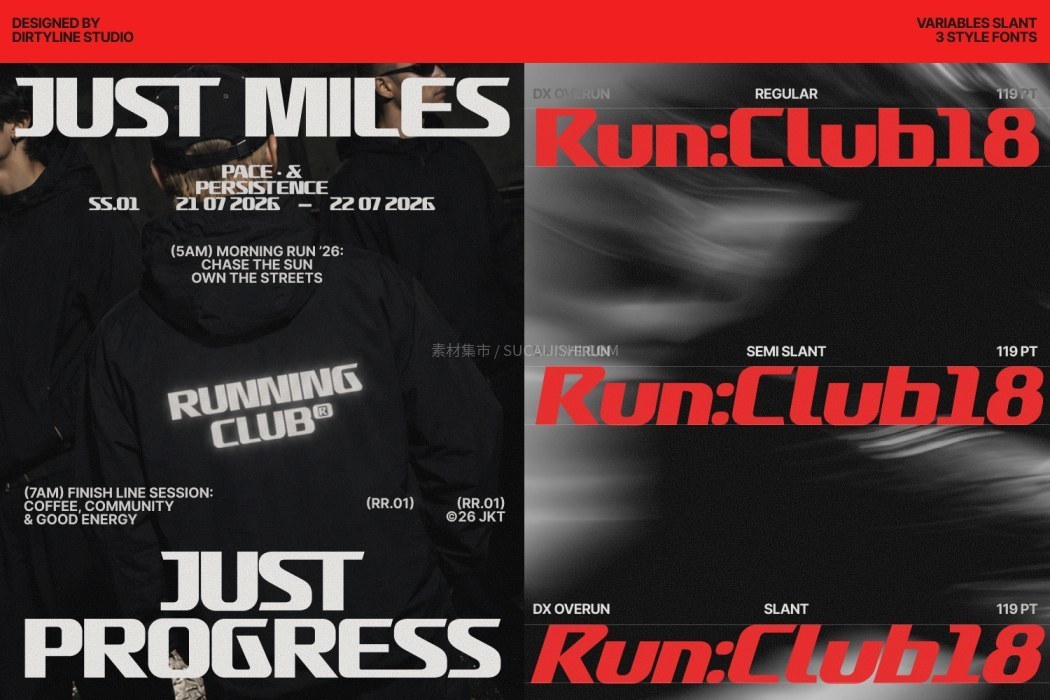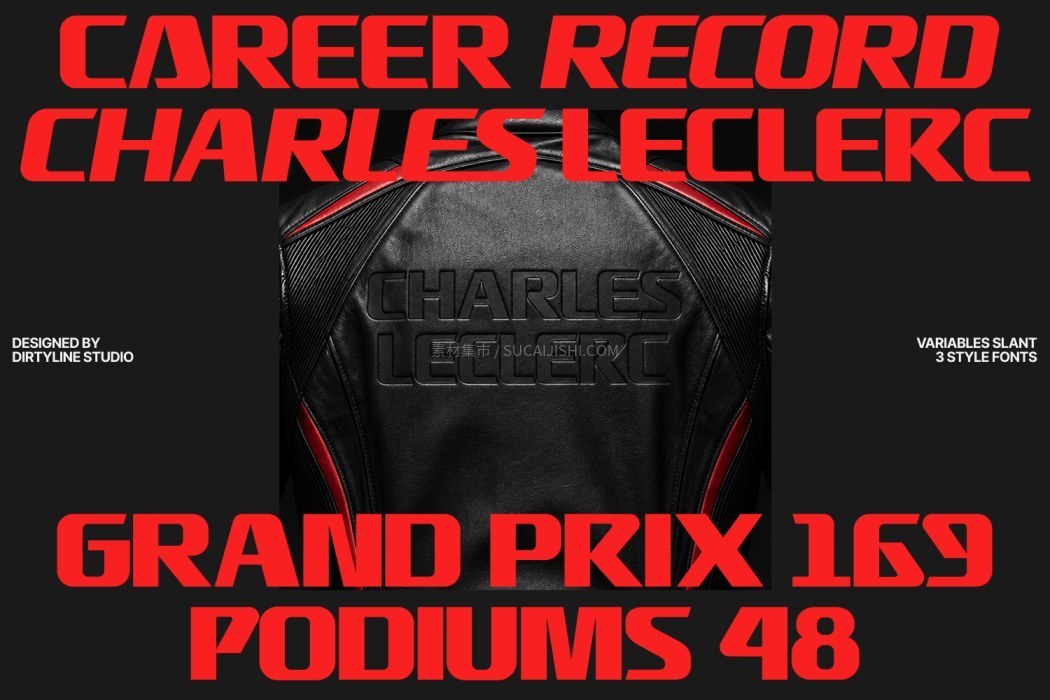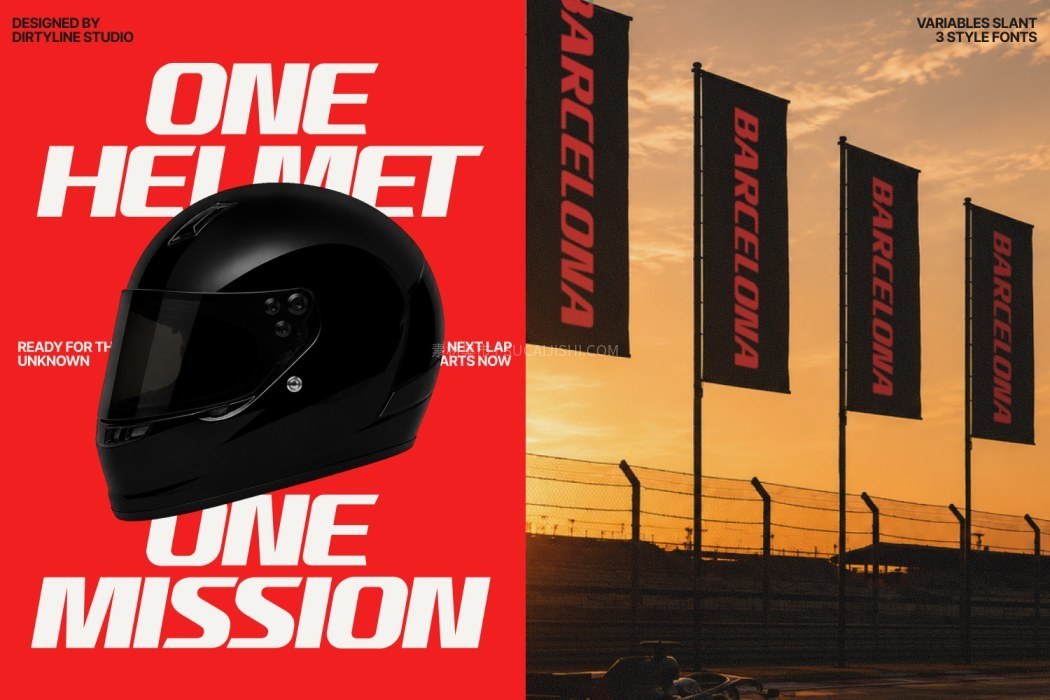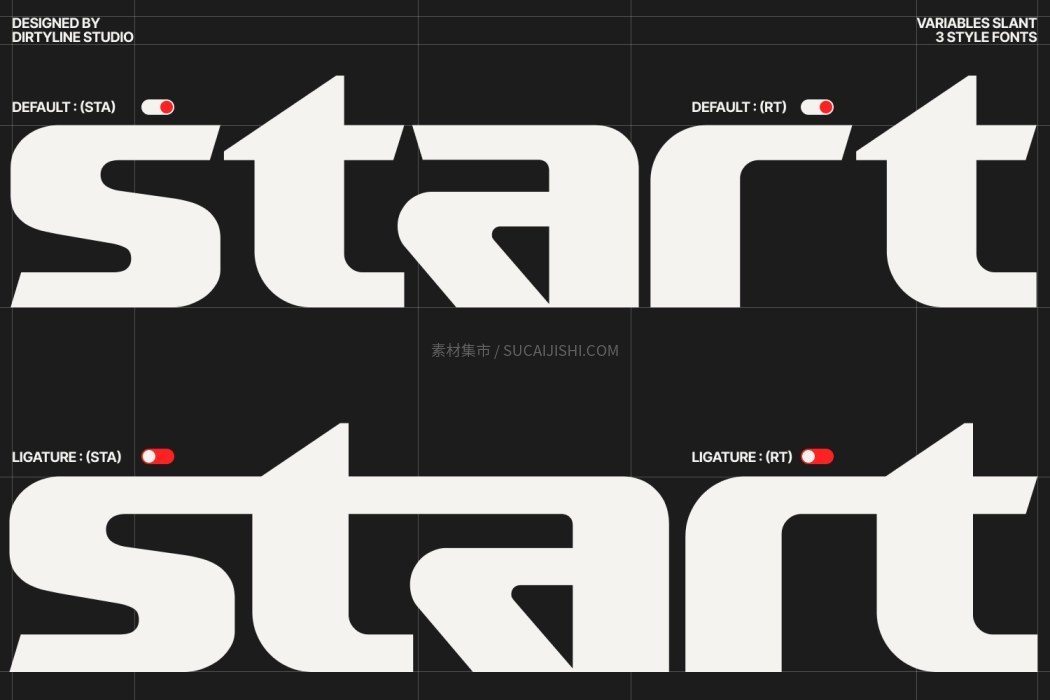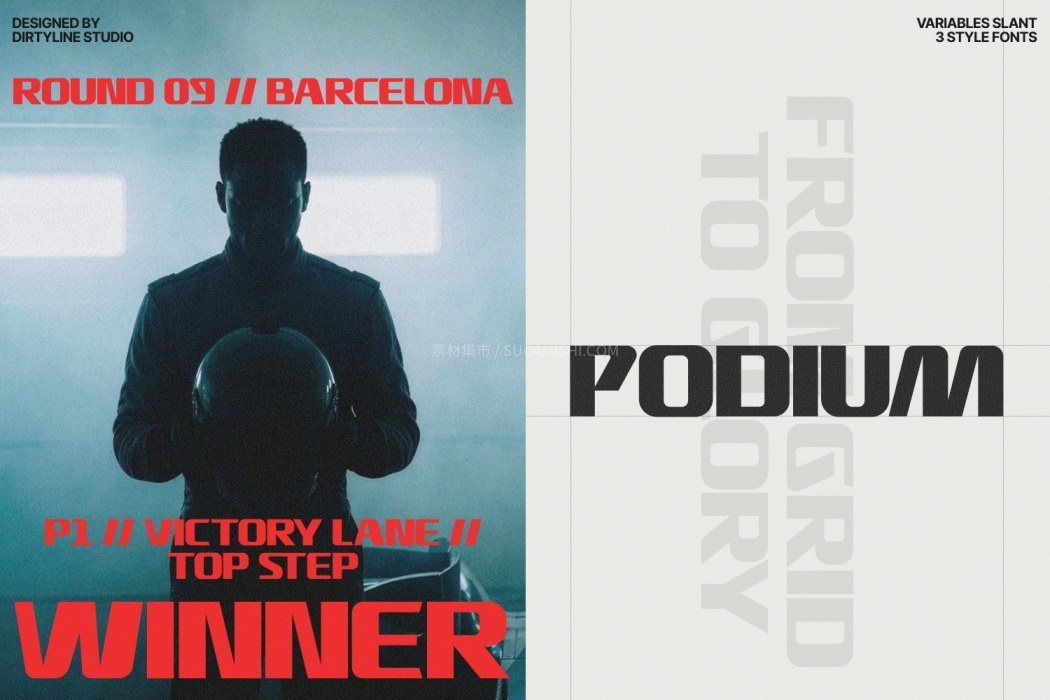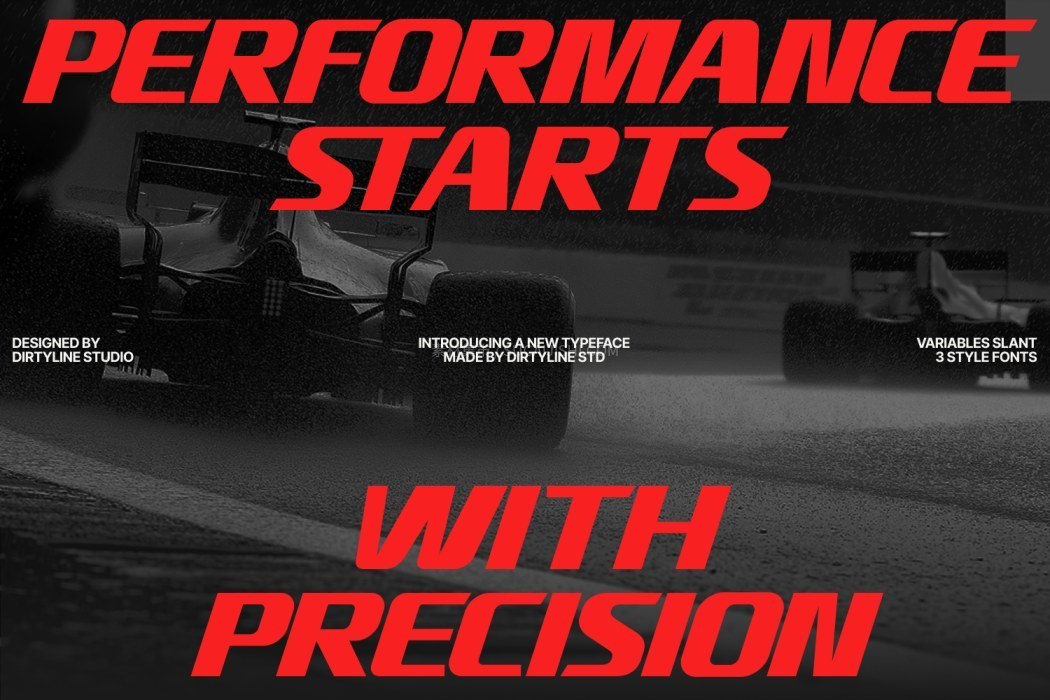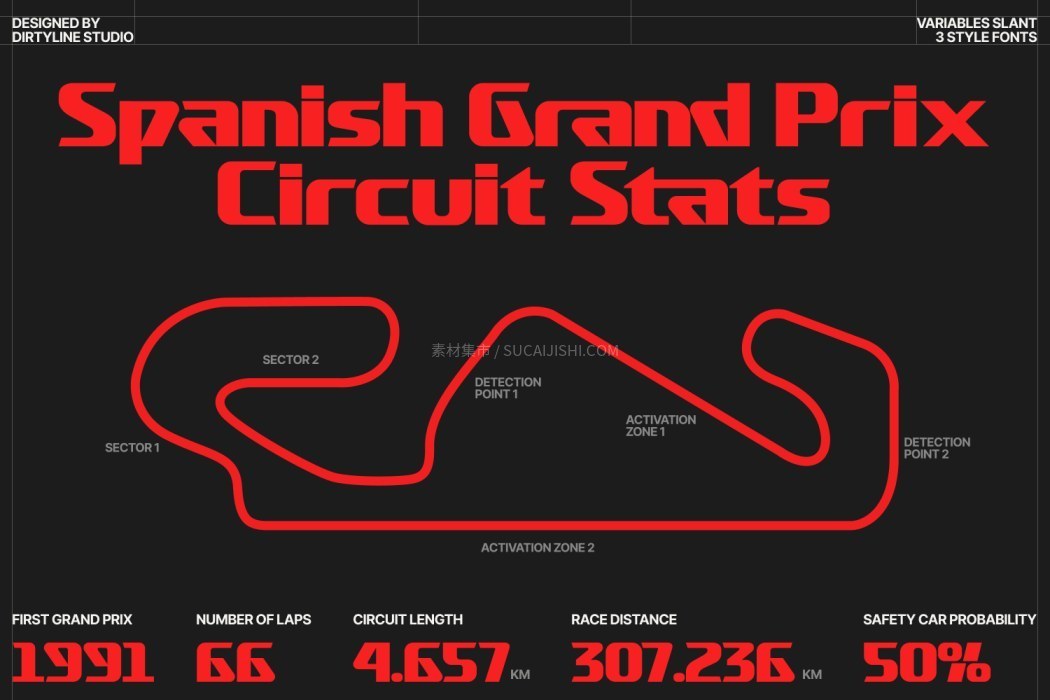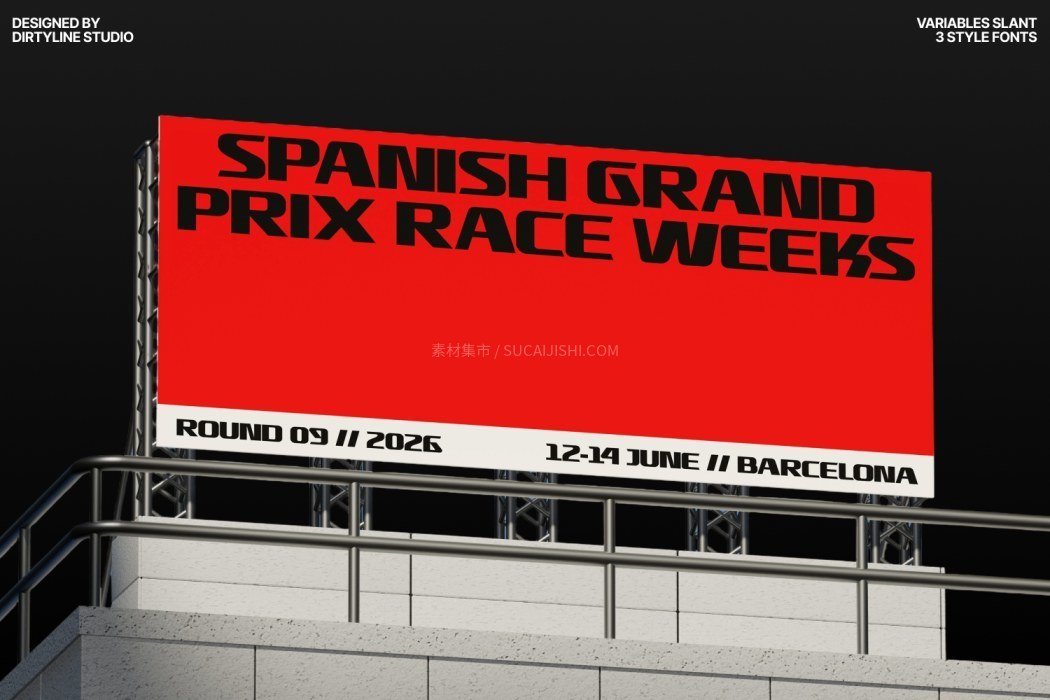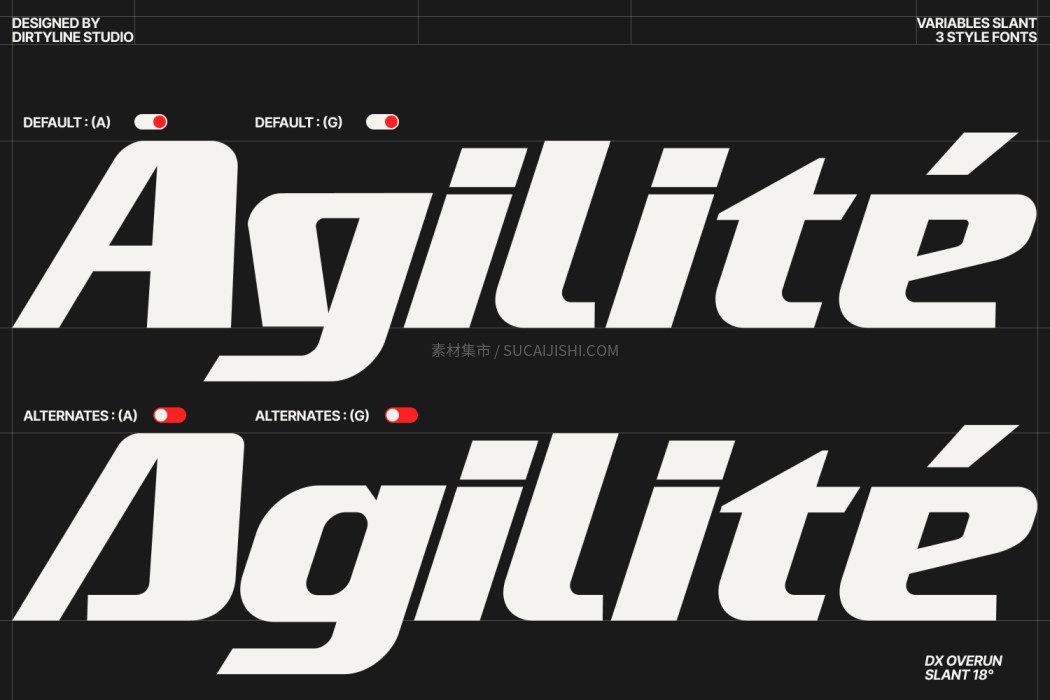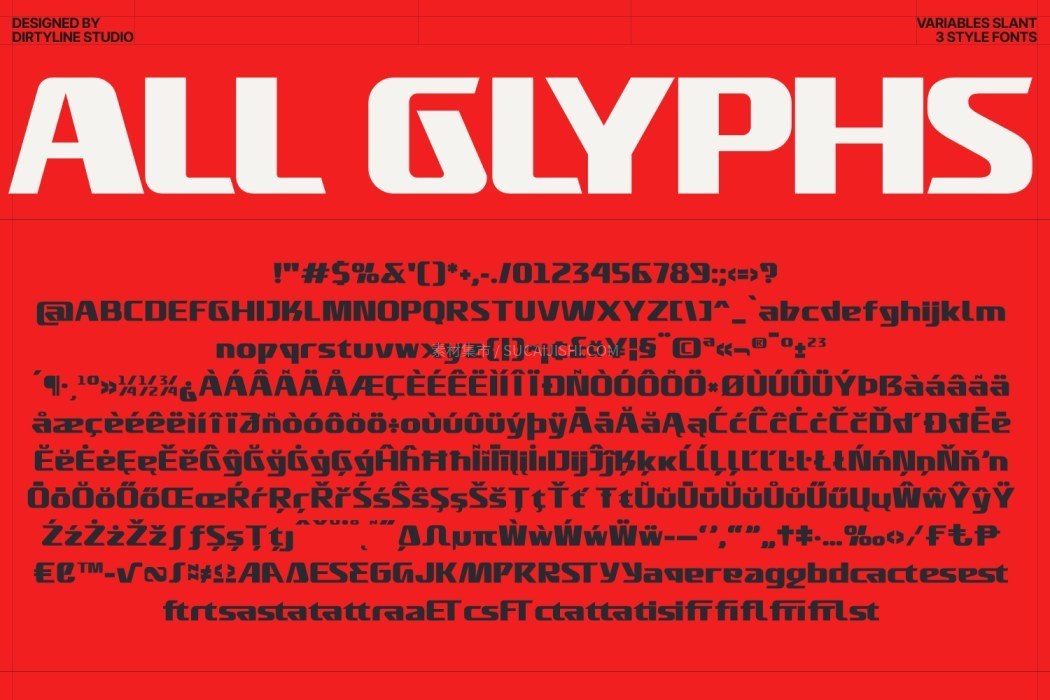
DX Overrun竞速机甲风赛车可变字体
这款字体简直把“速度与激情”刻在了DNA里!它不仅自带一种霸气侧漏的高性能机甲感,还有宽阔厚重的字形和充满空气动力学的倾斜角度,锐利的几何切割让每一个字母都充满爆发力!这套全能字体包含了 3 种精美样式,并且支持超灵活的可变倾斜角度调节,还带有多语言支持和独特的风格替代字形。不管是做赛车运动Logo、电竞赛事海报、汽车品牌视觉,还是潮牌运动服、游戏UI和酷炫的社交媒体排版,它都能轻松拿捏,视觉冲击力直接拉满!想要让你的设计作品拥有未来科技感和迅捷动感,这款宝藏运动字体千万别错过,赶紧马住用起来吧!